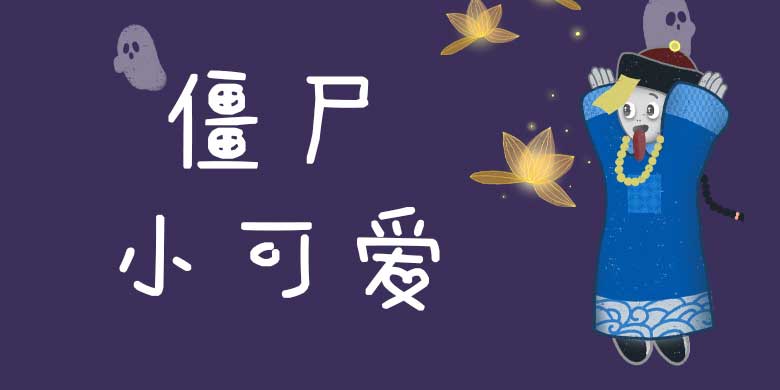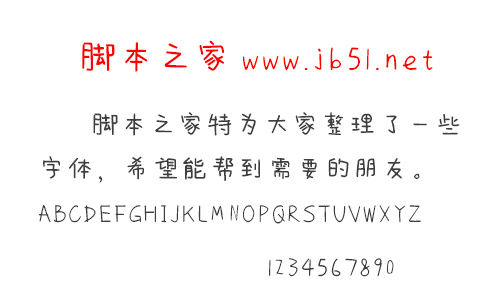
方正手跡-僵尸小可愛(ài)這款字體筆畫簡(jiǎn)潔,方圓兼?zhèn)洌中沃袑m緊湊,大小錯(cuò)落,重心左右搖擺,俏皮可愛(ài)。適用于少兒類的書刊、品牌廣告和產(chǎn)品包裝設(shè)計(jì),綜藝漫畫用字,以及社交網(wǎng)絡(luò)的個(gè)性化用字,歡迎喜歡方正手跡-僵尸小可愛(ài)字體的朋友前來(lái)下載使用。